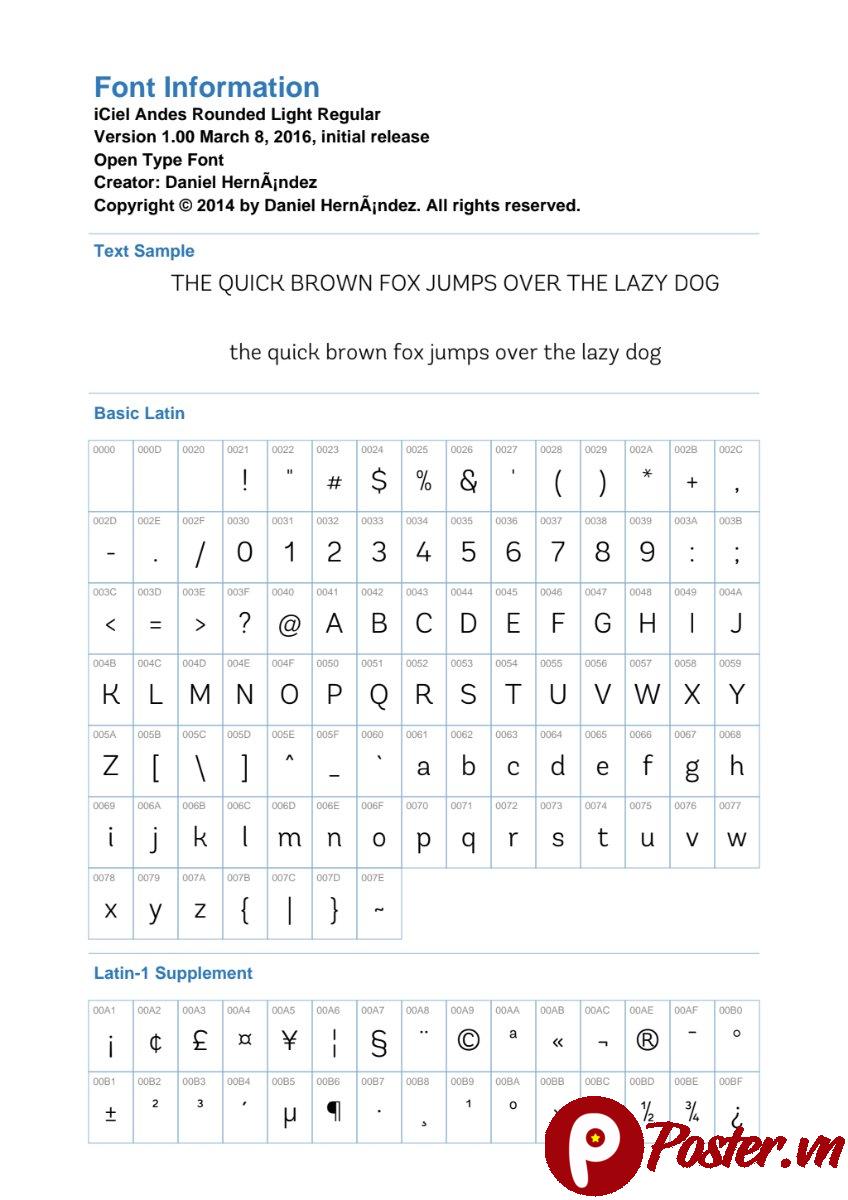
Font Andes Rounded Light Regular
Giới Thiệu Font Andes Rounded Light Regular
Font Andes Rounded Light Regular là một kiểu chữ hiện đại, thanh lịch và thân thiện, được thiết kế bởi Daniel Hernández. Với các góc bo tròn nhẹ nhàng, font chữ này mang lại cảm giác mềm mại, dễ chịu nhưng vẫn giữ được sự rõ ràng và chuyên nghiệp. Đây là lựa chọn lý tưởng cho nhiều loại hình thiết kế, từ ấn phẩm in ấn đến giao diện kỹ thuật số.
Đặc Điểm Nổi Bật của Font Andes Rounded Light Regular
• Thiết kế hiện đại: Các đường nét tinh tế, góc bo tròn tạo nên vẻ ngoài mềm mại, thân thiện.
• Dễ đọc: Dù là chữ hoa hay chữ thường, font đều đảm bảo độ rõ ràng, dễ đọc trên mọi kích thước.
• Đa năng: Phù hợp cho tiêu đề, nội dung văn bản, logo, branding, website, ứng dụng di động và nhiều hơn nữa.
• Hỗ trợ đa ngôn ngữ: Bao gồm các ký tự Latin cơ bản và bổ sung Latin-1, đáp ứng nhu cầu thiết kế đa dạng.
Ứng Dụng của Font Andes Rounded Light Regular trong Thiết Kế
Font Andes Rounded Light Regular là một công cụ mạnh mẽ cho các nhà thiết kế đồ họa, marketing và những ai yêu thích sự sáng tạo. Dưới đây là một số ứng dụng phổ biến:
Thiết Kế Logo và Nhận Diện Thương Hiệu
Với vẻ ngoài hiện đại và thân thiện, font này rất thích hợp để tạo logo cho các thương hiệu muốn truyền tải sự gần gũi, đổi mới và chuyên nghiệp. Sự mềm mại của các góc bo tròn giúp logo trở nên dễ tiếp cận và đáng nhớ. Poster.vn khuyến khích bạn thử nghiệm font này để tạo ra những bộ nhận diện thương hiệu độc đáo, giúp doanh nghiệp của bạn nổi bật trên thị trường.
Ấn Phẩm Quảng Cáo và Marketing
Từ poster, banner, flyer đến các ấn phẩm kỹ thuật số, Font Andes Rounded Light Regular giúp thông điệp của bạn trở nên rõ ràng và hấp dẫn. Độ dễ đọc cao của font đảm bảo rằng khách hàng sẽ dễ dàng tiếp nhận thông tin, trong khi vẻ đẹp thẩm mỹ của nó sẽ thu hút sự chú ý. Sử dụng font này cho các chiến dịch quảng cáo của bạn để tạo ra sự khác biệt và hiệu quả.
Thiết Kế Website và Ứng Dụng Di Động
Trong môi trường kỹ thuật số, việc lựa chọn font chữ phù hợp là cực kỳ quan trọng để đảm bảo trải nghiệm người dùng tốt. Font Andes Rounded Light Regular với thiết kế sạch sẽ và dễ đọc là lựa chọn tuyệt vời cho các tiêu đề, nút bấm và nội dung văn bản trên website hay ứng dụng di động. Nó giúp giao diện của bạn trở nên hiện đại, thân thiện và dễ sử dụng.
Sách Báo và Tạp Chí
Đối với các ấn phẩm in ấn như sách, báo, tạp chí, việc sử dụng một font chữ dễ đọc và có tính thẩm mỹ cao là điều cần thiết. Font Andes Rounded Light Regular đáp ứng tốt cả hai tiêu chí này, giúp độc giả có trải nghiệm đọc thoải mái và dễ chịu. Các nhà xuất bản có thể tin tưởng vào chất lượng của font này để nâng cao giá trị thẩm mỹ cho các ấn phẩm của mình.
Kết Hợp Với Các Font Khác
Font Andes Rounded Light Regular có thể kết hợp tốt với nhiều loại font khác nhau. Để tạo sự cân bằng và hài hòa, bạn có thể ghép nối nó với một font serif cổ điển hoặc một font sans-serif đậm nét hơn cho các tiêu đề phụ hoặc điểm nhấn. Sự linh hoạt này cho phép bạn tạo ra các thiết kế đa dạng và phong phú.
Lựa Chọn Kích Thước và Màu Sắc
Với thiết kế Light Regular, font này phù hợp cho cả văn bản nhỏ và lớn. Tuy nhiên, để đạt hiệu quả tốt nhất, hãy đảm bảo kích thước font đủ lớn để dễ đọc, đặc biệt là trên các nền màu tương phản. Về màu sắc, font Andes Rounded Light Regular có thể sử dụng với nhiều bảng màu khác nhau, từ tông màu trung tính đến màu sắc tươi sáng, tùy thuộc vào phong cách thiết kế tổng thể của bạn.
Font Andes Rounded Light Regular có hỗ trợ tiếng Việt không?
Font này hỗ trợ các ký tự Latin cơ bản và bổ sung Latin-1. Để biết chính xác về hỗ trợ tiếng Việt, bạn nên kiểm tra bảng ký tự đầy đủ hoặc thử nghiệm trực tiếp.